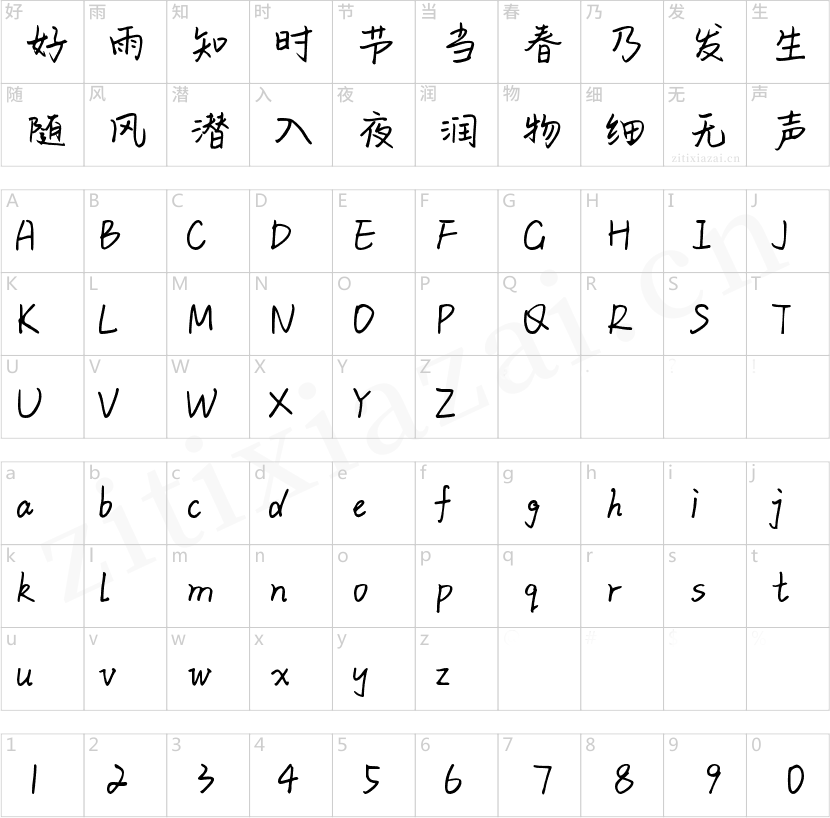
Aa我的晴天女孩
Aa我的晴天女孩字体
Aa我的晴天女孩是一款非常具有艺术性的字体,它的设计灵感来源于对古典艺术的研究,同时又融入了现代字体设计的元素。字形优美,笔画粗细变化自然,给人以大气、典雅的感觉。Aa我的晴天女孩是一款既传统又现代的字体,它的设计充满艺术感,美观大方,实用性也非常强。无论是对于设计师还是对于普通读者来说,都是一种非常不错的字体选择。Aa我的晴天女孩适合用于具有艺术感的场合,比如海报、宣传单张、书籍封面等。由于其字形流畅且具有动态感,也适合用于大量的文本排版,如报纸、杂志等。